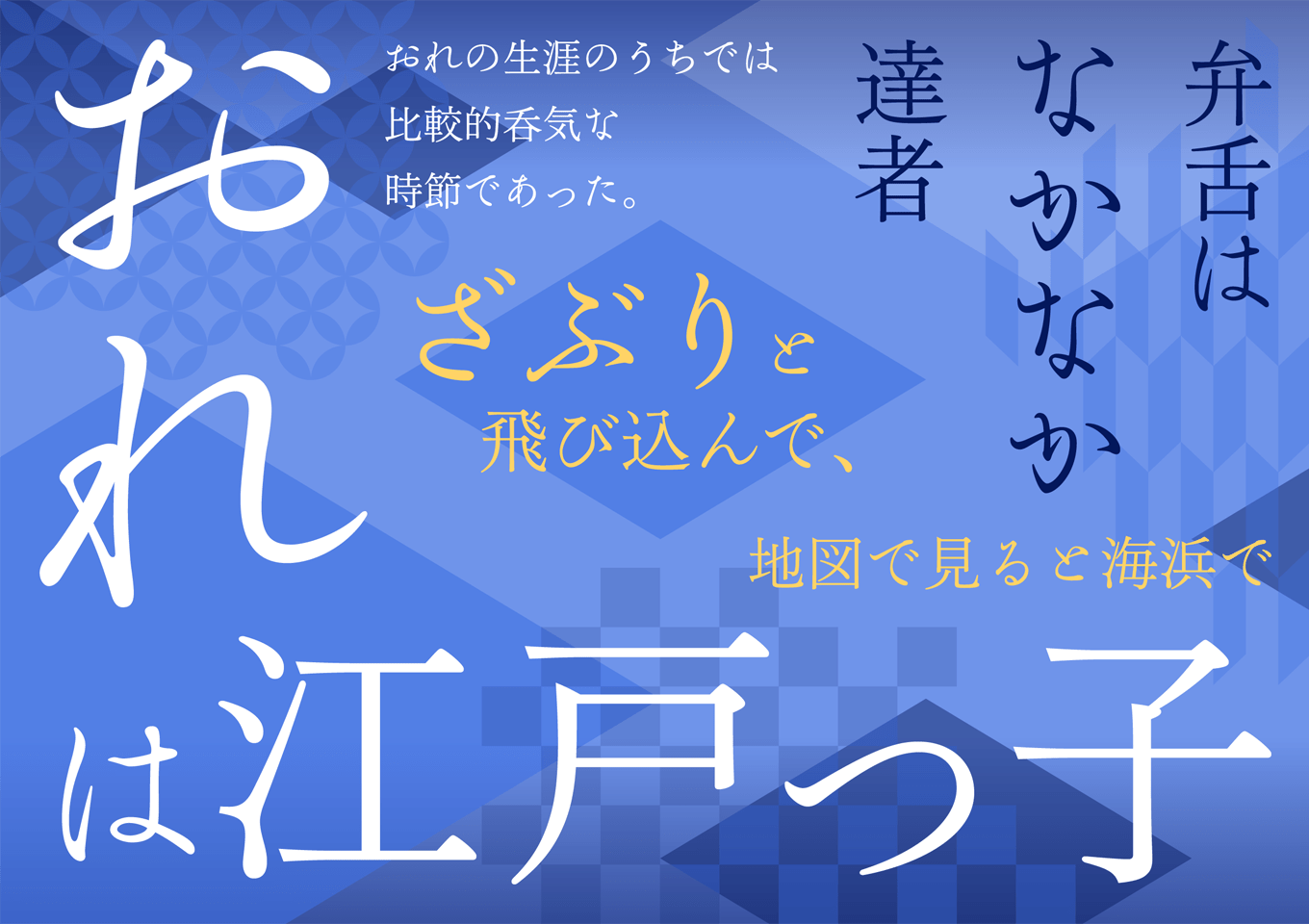
「文游明朝体」の漢字に、小粋な雰囲気漂う「古雅かな」を組み合わせた総合書体です。 江戸時代の刊本にインスパイアされたかなは、文字によって空間の広さが大きく異なり、右上がりが強調されたデザインです。クラシカルな雰囲気を演出できる本文組版の利用はもちろん、見出しとしてお使いいただくことで力強い印象を与えることができます。